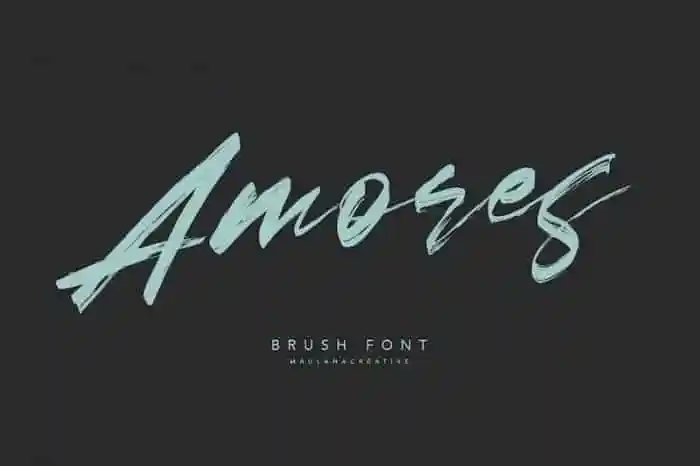
A Amores Brush Font é uma fonte desenhada à mão com estilo brush, apresentando linhas fluidas que são perfeitas para dar um toque sofisticado e moderno a qualquer texto. Com seu traçado elegante e luxuoso, esta fonte script dá um novo tom de elegância às suas criações digitais. Desenhada por Maulana Creative na plataforma 99designs, ela oferece uma opção única para aqueles que buscam estilizar seus designs sem abrir mão do conforto visual. Seja em um e-mail personalizado ou em um design de produto, a Amores Brush Font é sua chave para destacar-se no mercado dos recursos gráficos digitais com estilo único.